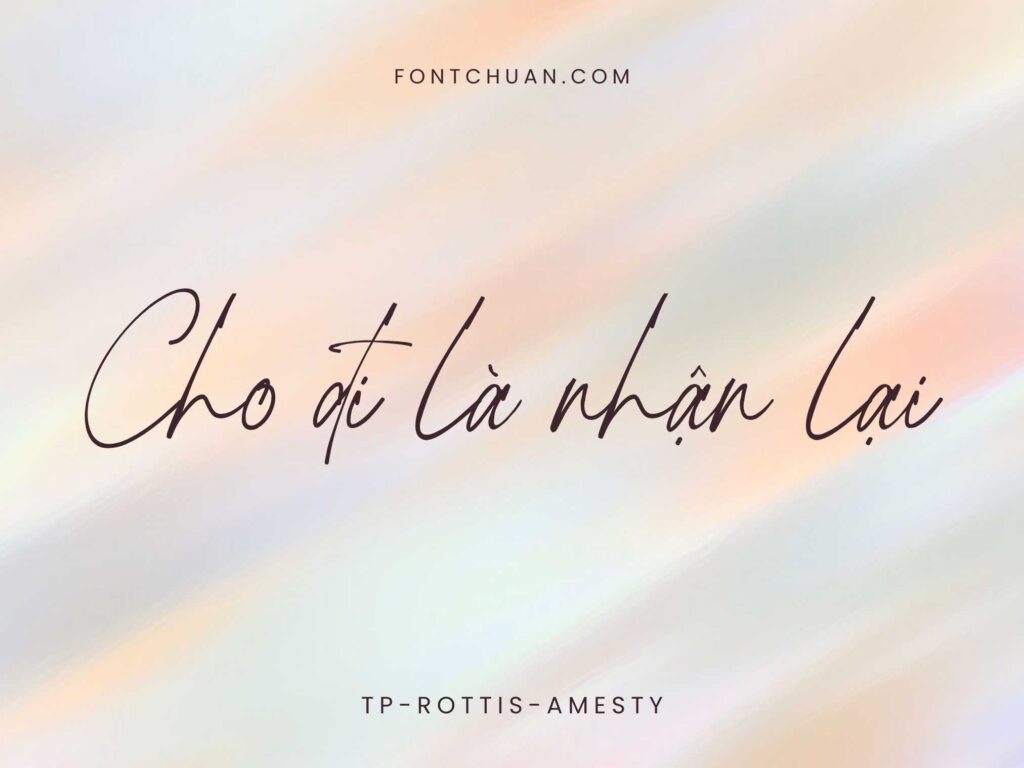
Font TP Rottis Amesty Việt Hóa
Tác giả Font: Create Big Supply
Rottis Amesty là một font chữ viết tay hiện đại, được thiết kế bởi Creatype Studio. Với phong cách uyển chuyển và mềm mại, font này còn được xem như một dạng Font chữ ký, mang lại cảm giác tự nhiên và tinh tế cho các dự án thiết kế. Nhờ đặc điểm này, Rottis Amesty rất phù hợp cho các sản phẩm như thiệp mời, logo, tiêu đề và những thiết kế cần sự gần gũi nhưng vẫn giữ nét sang trọng. Font đã được Việt hóa để hỗ trợ tiếng Việt bởi Tuỳn Pucca, giúp người dùng Việt Nam dễ dàng sử dụng trong các dự án sáng tạo. Font này được sưu tầm và chia sẻ bởi thành viên của Font Chuẩn, đáp ứng nhu cầu sử dụng đa dạng trong cộng đồng thiết kế.
Đặc điểm thiết kế của Rottis Amesty bao gồm các nét chữ mượt mà và tự nhiên, tạo cảm giác thân thiện và gần gũi. Font này phù hợp cho các ứng dụng như thiệp mời, logo, tiêu đề và các dự án sáng tạo khác. Các ngành nghề phù hợp bao gồm quảng cáo, nghệ thuật và thiết kế đồ họa.